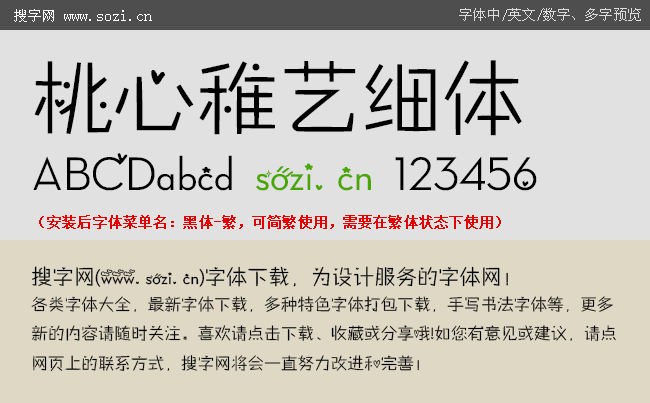
桃心稚藝細(xì)體(ST Heiti-Light)
搜字網(wǎng)提供一款可愛卡通風(fēng)格的手機中文字體下載,名叫桃心稚藝細(xì)體,這款手機字體以稚藝體為原形,在字體中嵌入了卡通心形圖案,稚藝體非常漂亮,帶有卡通風(fēng)味,活潑而不死板,加入卡通圖案后更加活潑可愛。喜歡的朋友就下載吧。